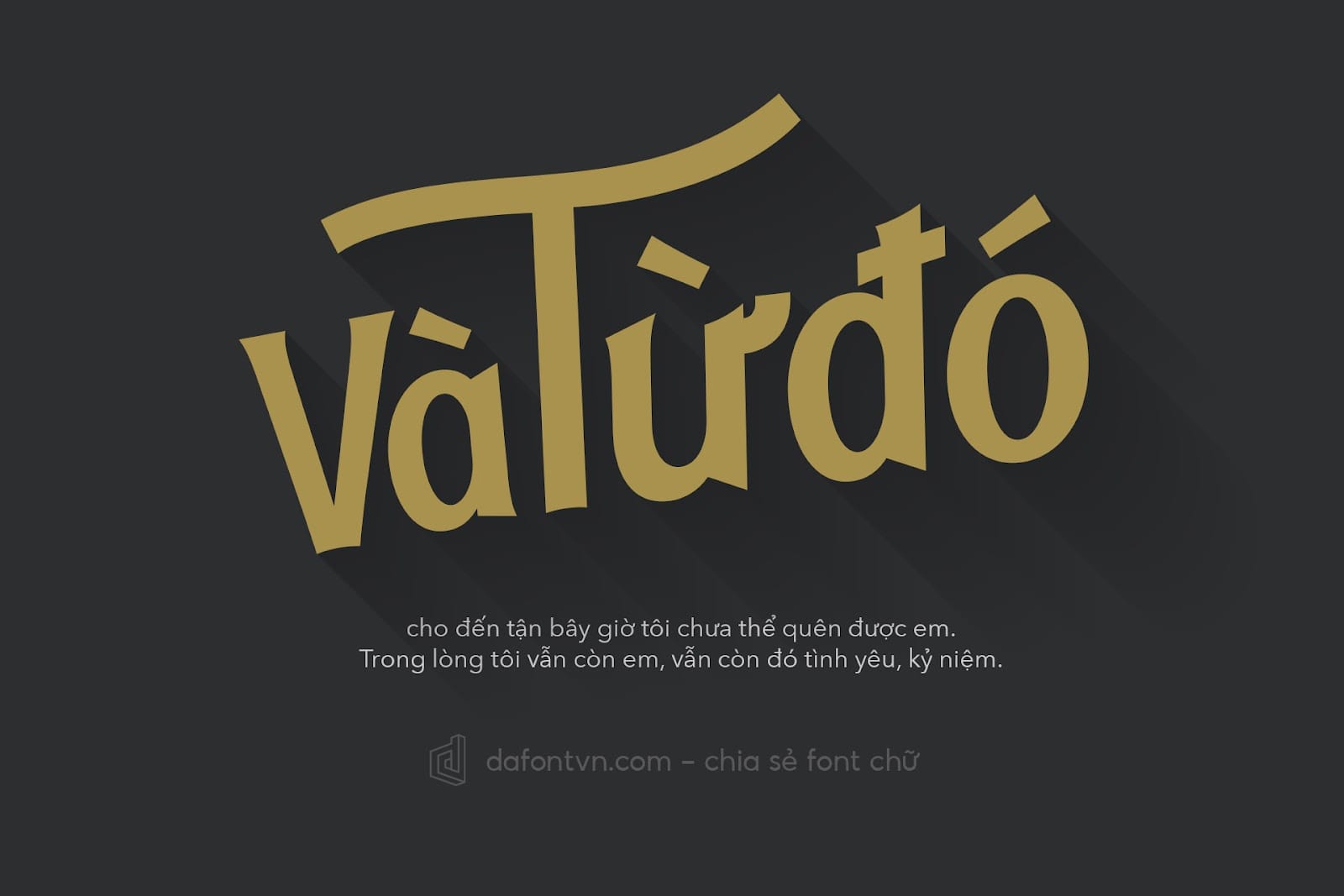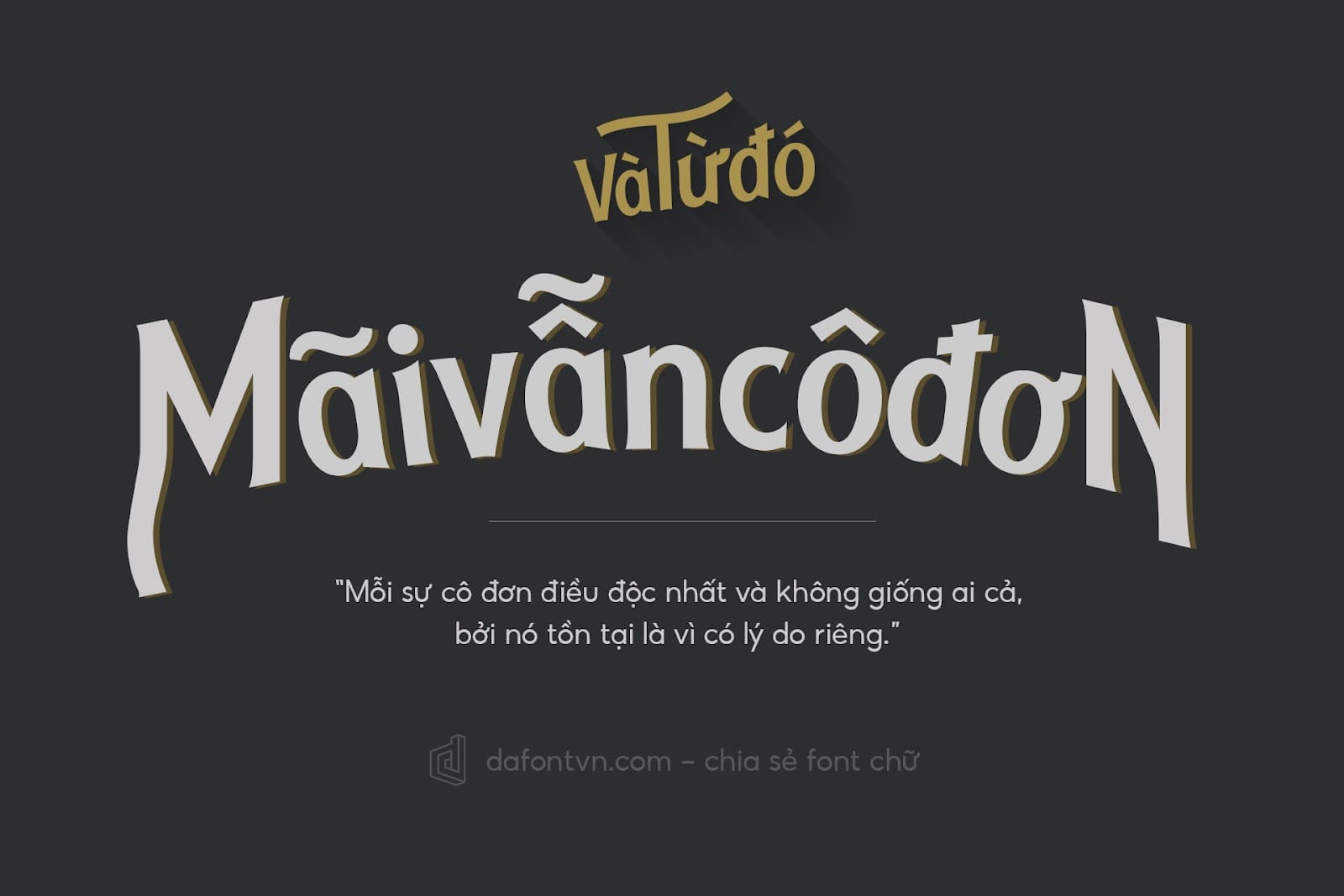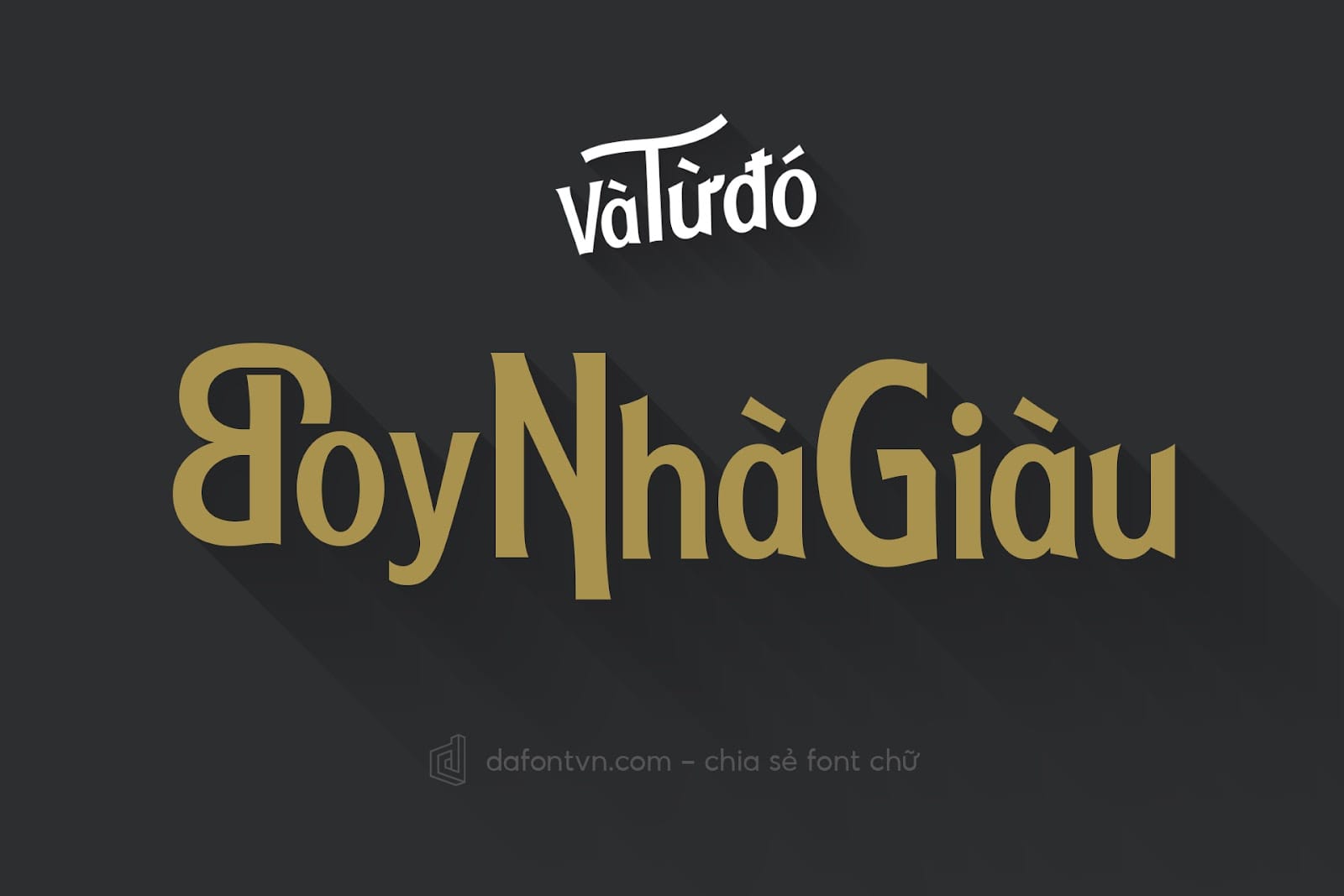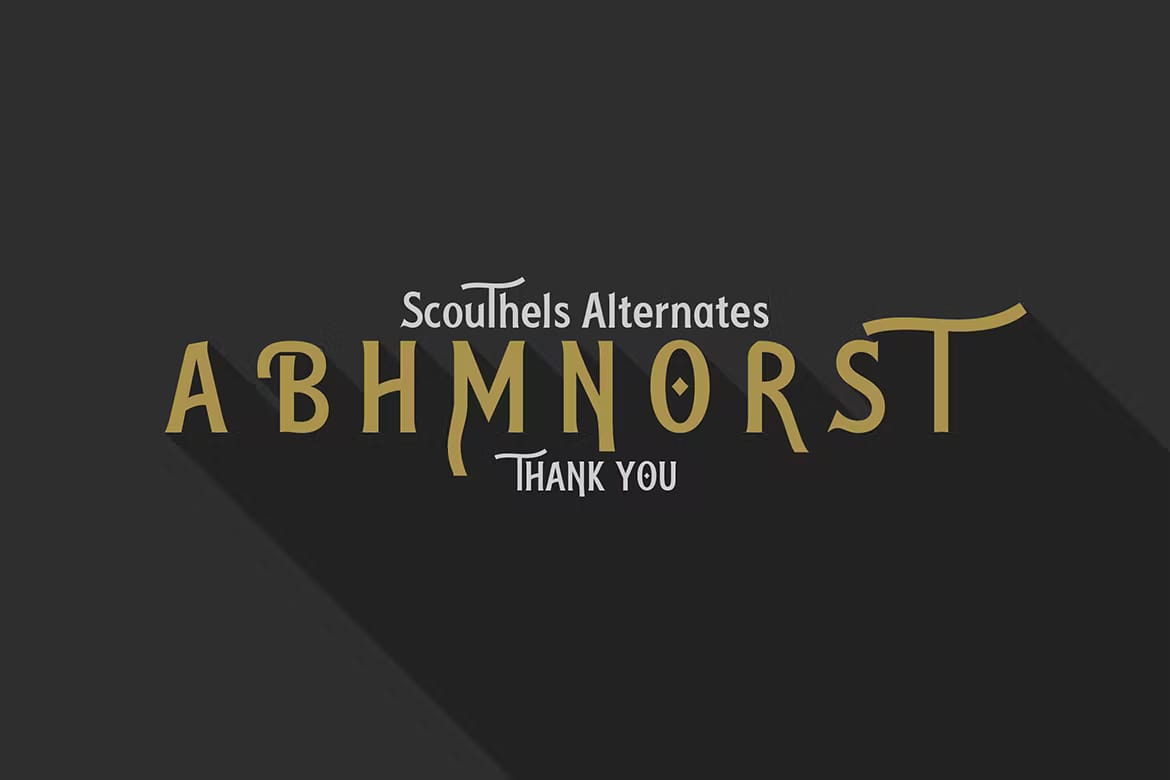
[Sans-Serif] Font Scouthels Việt Hóa
Font Scouthels Typeface là một kiểu font chữ cổ điển và hiện đại được thiết kế thủ công, kết hợp phong cách của kiểu chữ cổ điển với phong cách viết tay hiện đại. Font phù hợp cho rất nhiều các thiết kế như tiêu đề, bìa sách, typo hay bất kỳ thiết kế nào khác.
Scouthels Font được Việt Hóa đầy đủ, kerning cũng như tối ưu và chỉnh sửa lại để phù hợp với các dấu tiếng Việt.